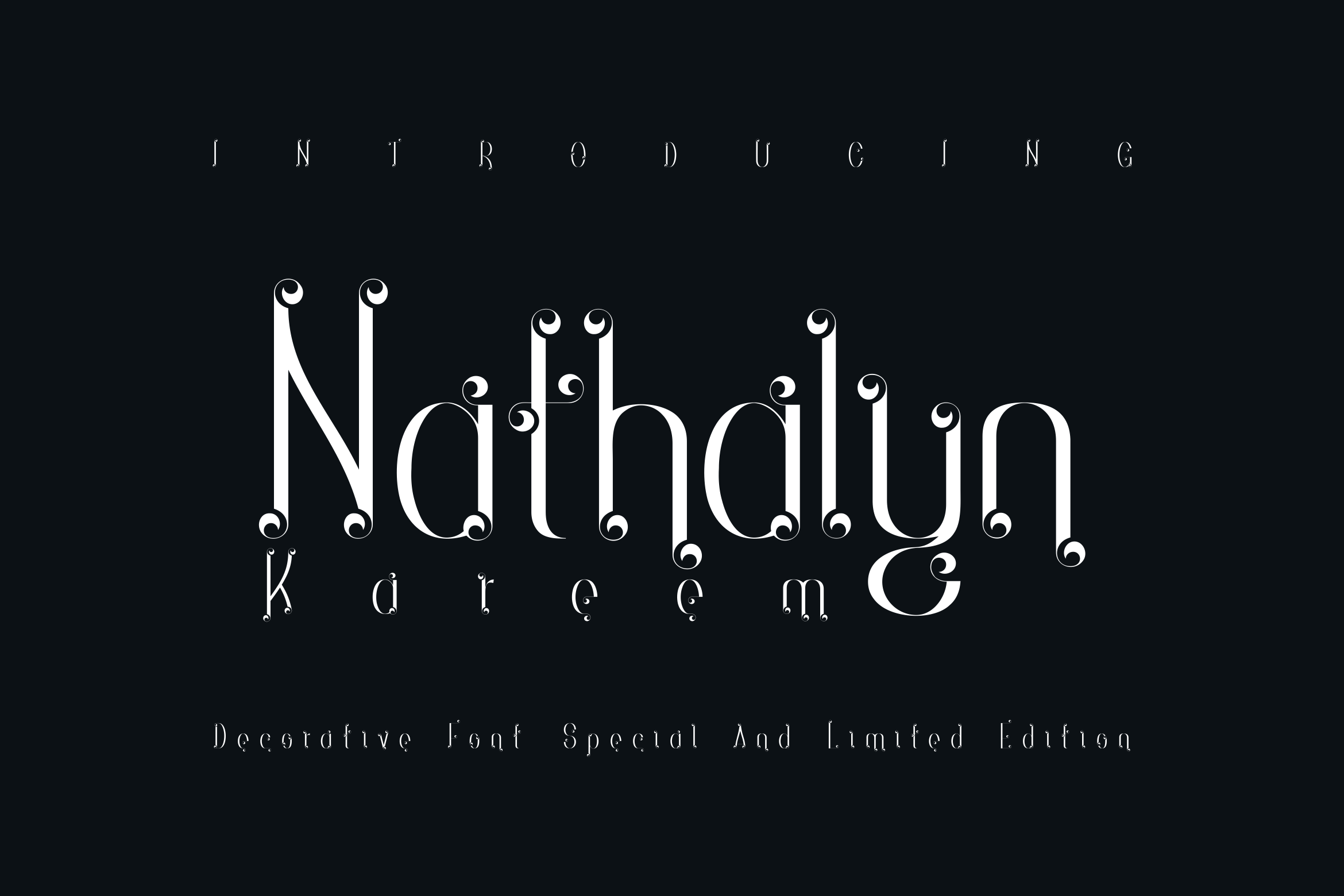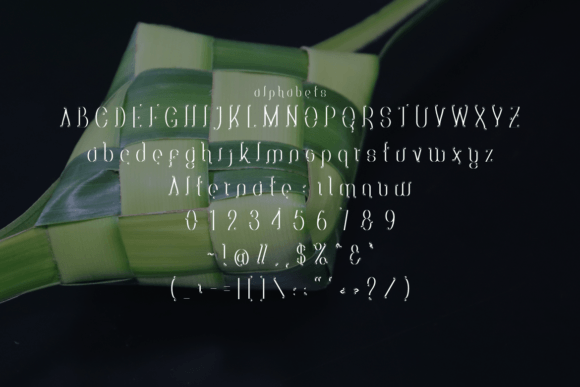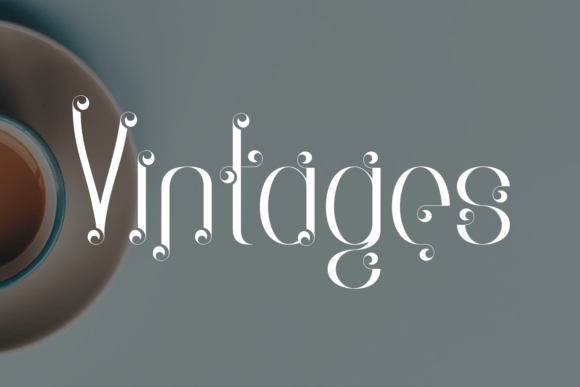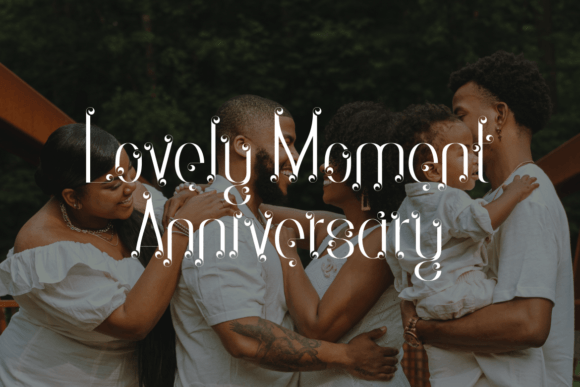
فونت Nathalyn Kareem انگلیسی
دانلود فونت Nathalyn Kareem انگلیسی Font ناتالین کریم |
| ⭐ مجموعه فونت | دانلود فونت انگلیسی ناتالین کریم Font Nathalyn Kareem |
| ⭐ توضیحات | فونتی است با ظاهری که دارای تزییناتی برای چیزهای مجلل مانند تعطیلات، روزهای خانوادگی و روزهای جشن در مورد لحظات شادی است.
این فونت به صورت ترکیبی و به عنوان فونت تبریک مانند کارت تبریک مناسب است و همچنین برای لحظات به یاد ماندنی آلبوم ها می توانند جایگزین اصلی در خاطرات زیبا با ترکیب این فونت باشند. |